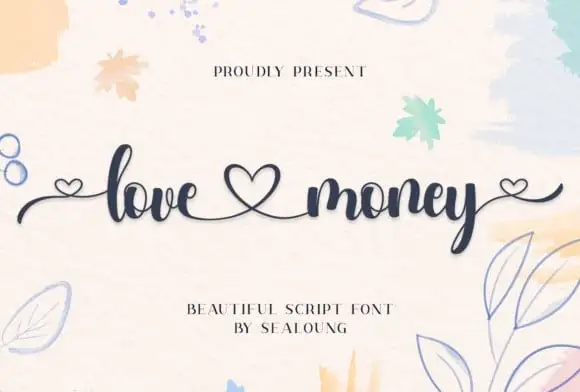
Love Money Calligraphy Font – Download Grátis
A Love Money Calligraphy Font é uma criação moderna que brilha tanto na parte inicial quanto na finalização, oferecendo um estilo romântico e elegante ao design. Desenvolvida pela Sealoung, essa fonte script adiciona detalhes encantadores em forma de coração que dão vida a esse belo fonte. Perfeita para aplicação em cartões de casamento, aniversários, mensagens personalizadas, selos e até mesmo logotipos ou cards de negócios, esta fonte traz um toque delicado à qualquer projeto gráfico que exige um toque autêntico. Suas linhas leves e suaves, assim como seus caracteres agradáveis e alternativas impressionantes, tornam o Love Money Calligraphy Font uma escolha ideal para designers em busca de algo único e encantador.